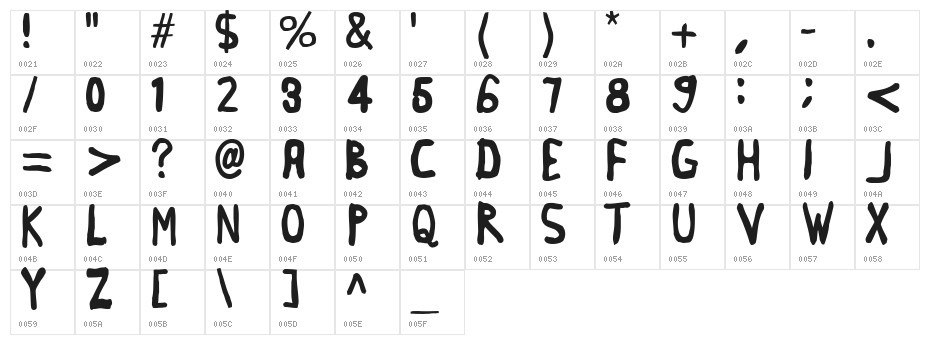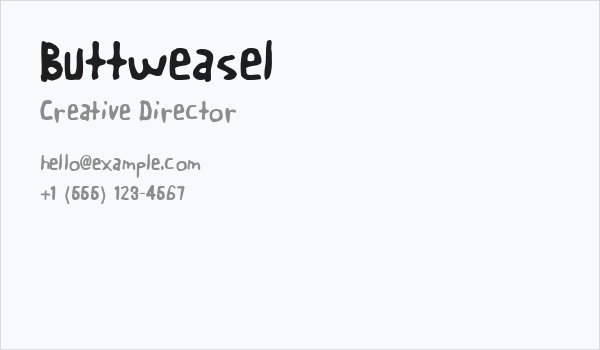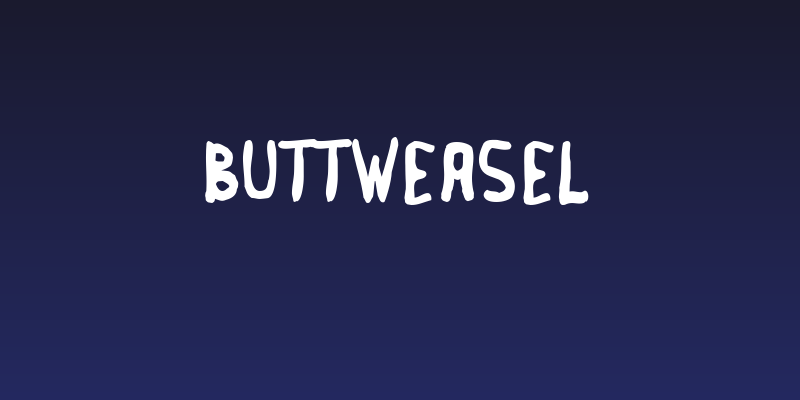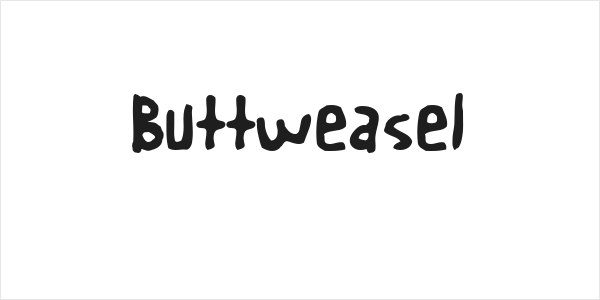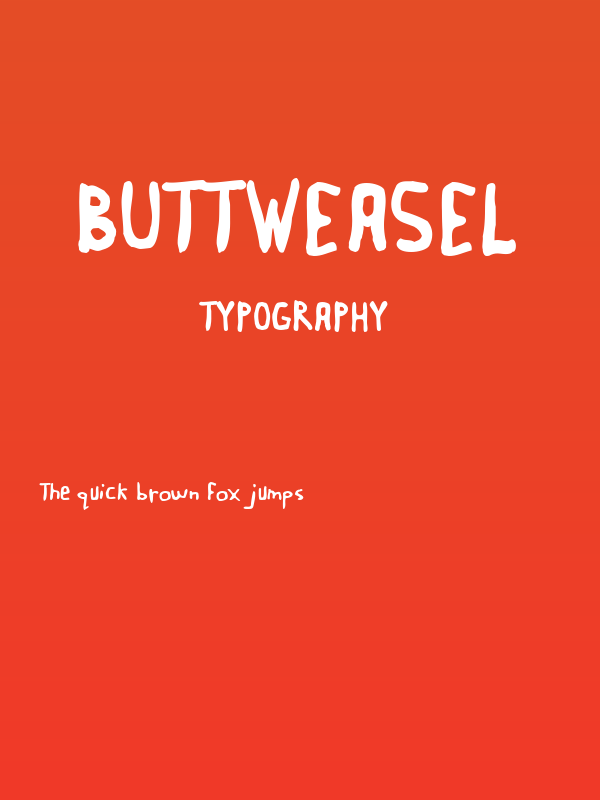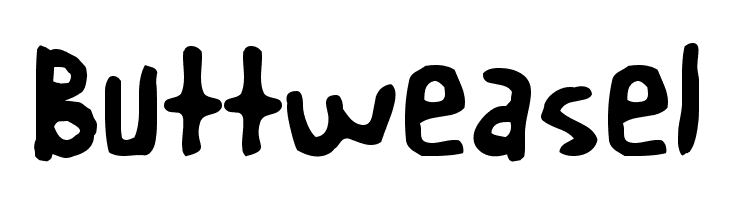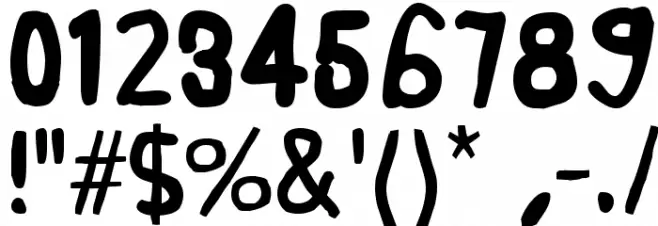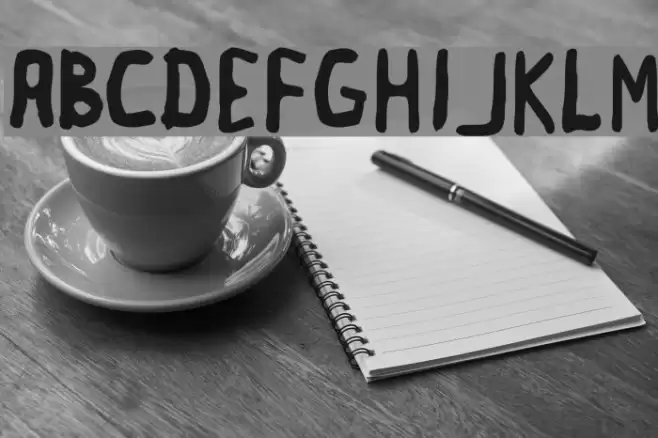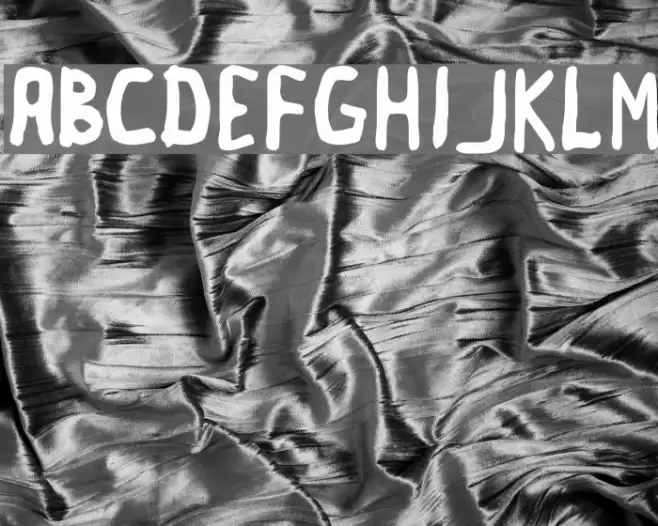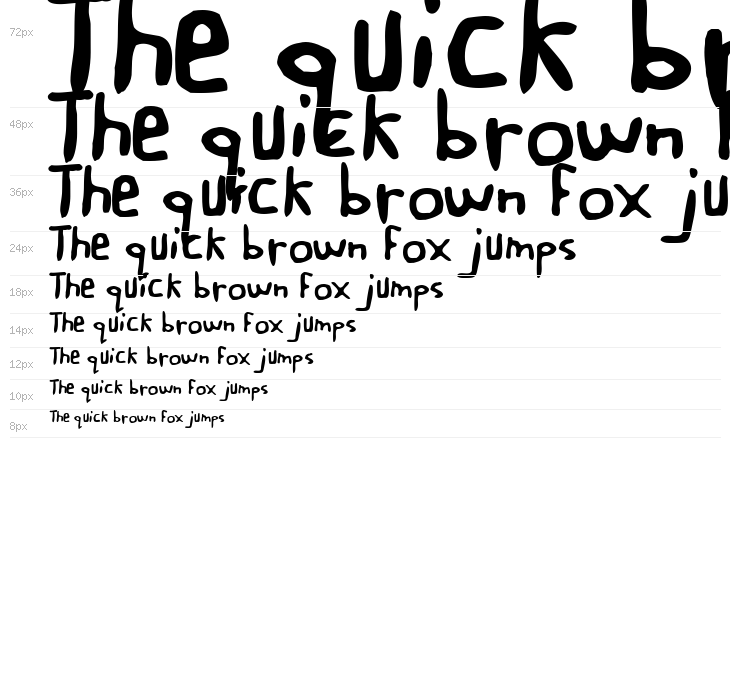
Buttweasel Font
| 用途 | Headlines, Logos, Informal Text |
| おすすめプロジェクト | Ideal for children's books, comic strips, greeting cards, and playful branding projects. |